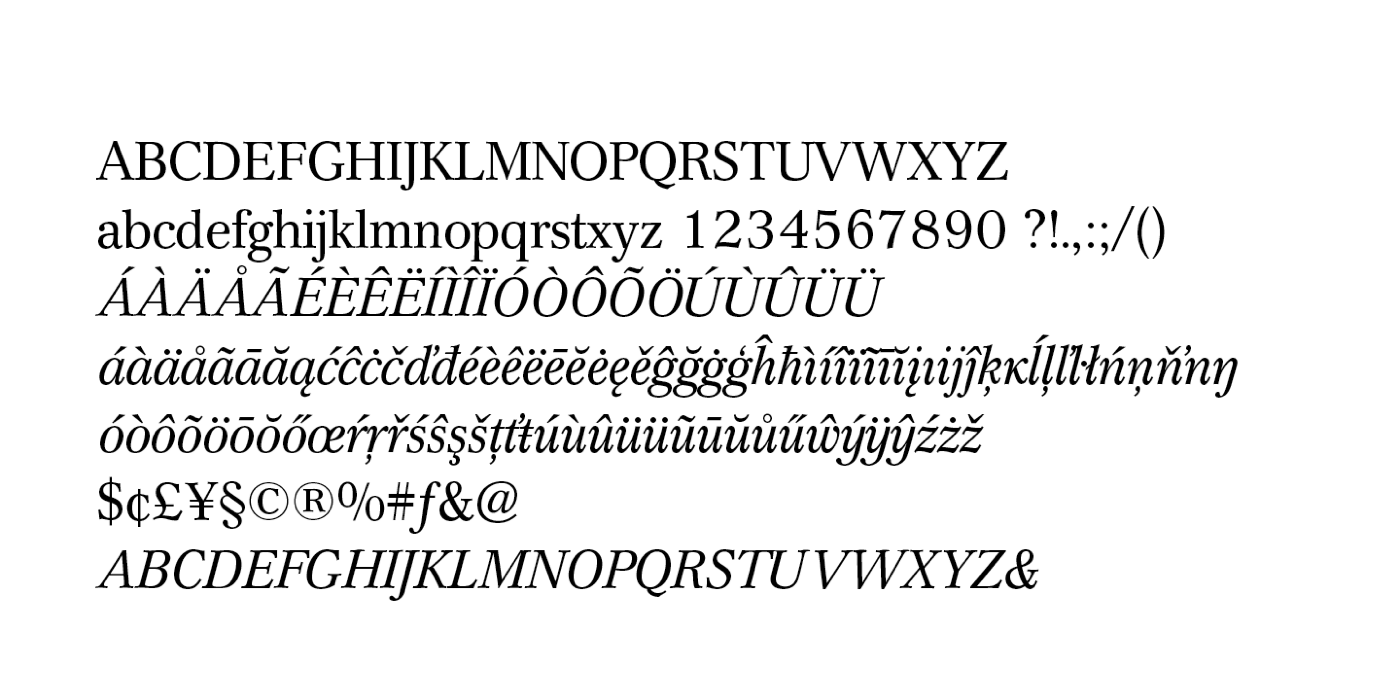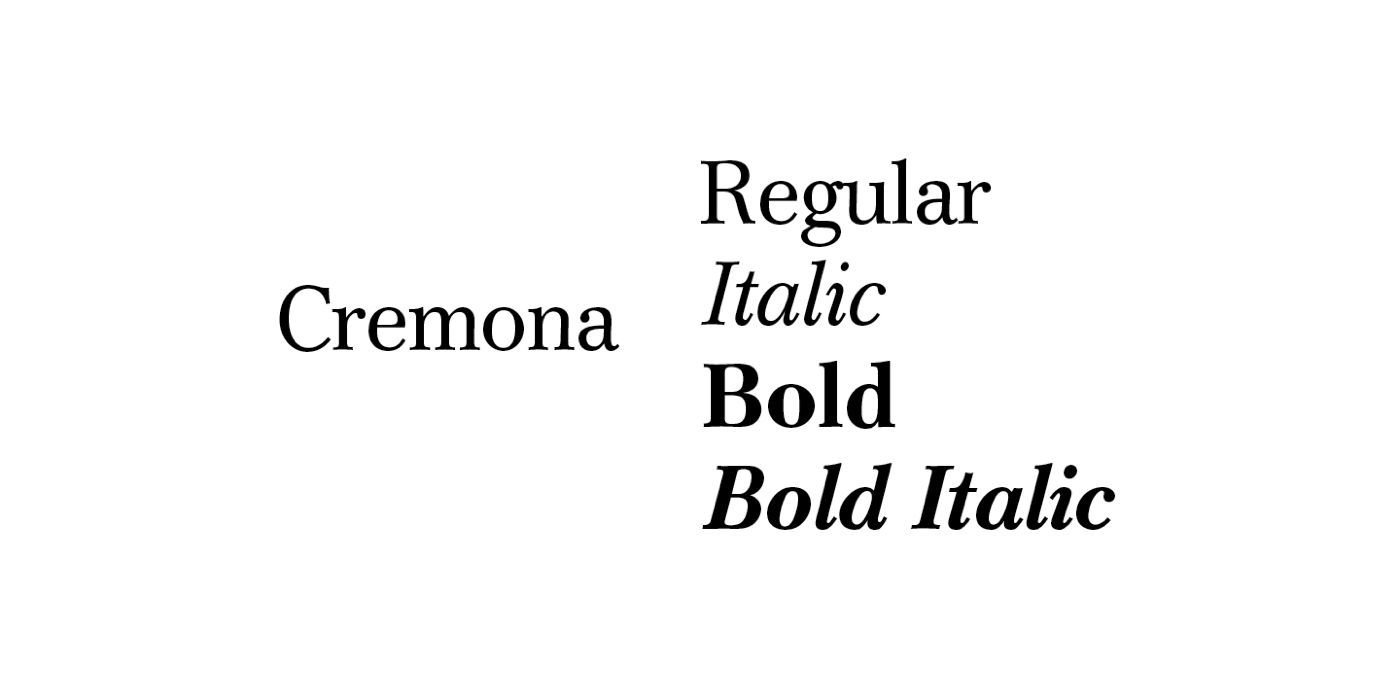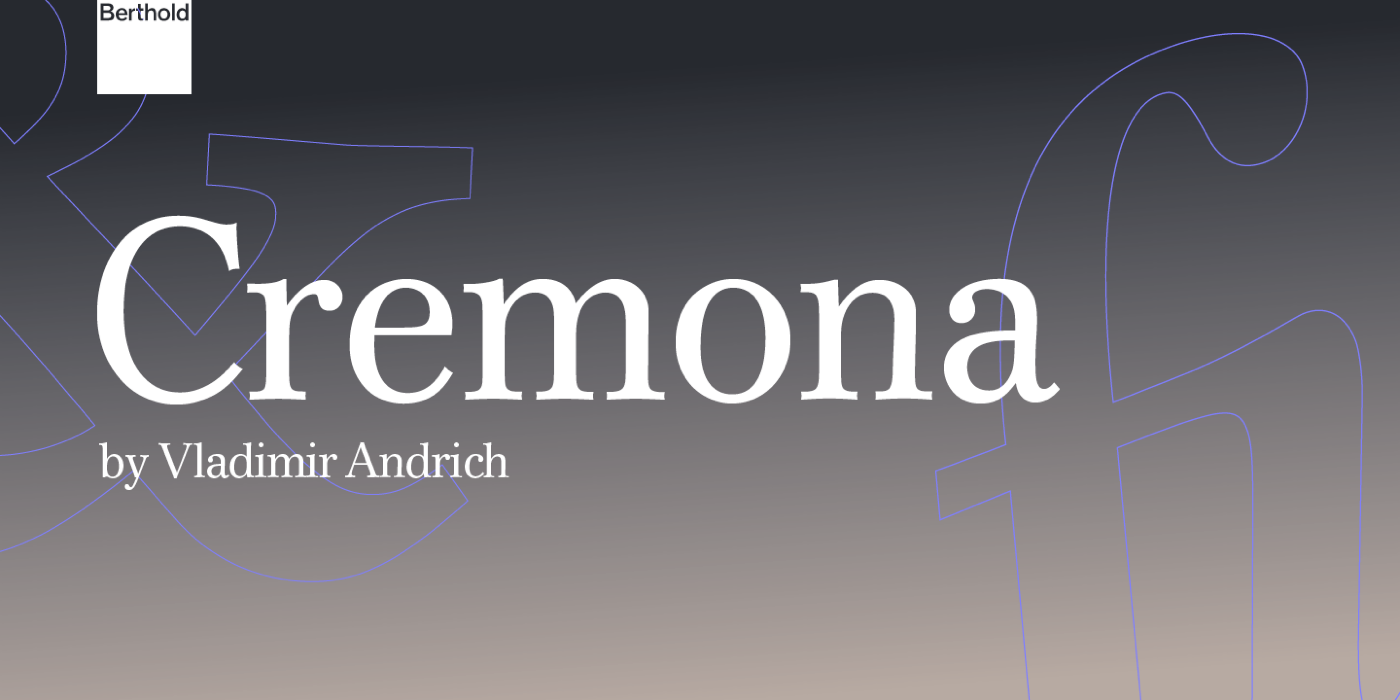
Wladimir Andrich entwickelte die Cremona ursprünglich für den Fotosatz-Anbieter Alphatype Corporation. Nachdem Berthold das Unternehmen Anfang der 1980er-Jahre übernahm, blieb die Schrift im Programm der H. Berthold AG. Eine digitale Version mit erweiterter lateinischer Belegung und Kapitälchen ist heute über Monotype verfügbar.